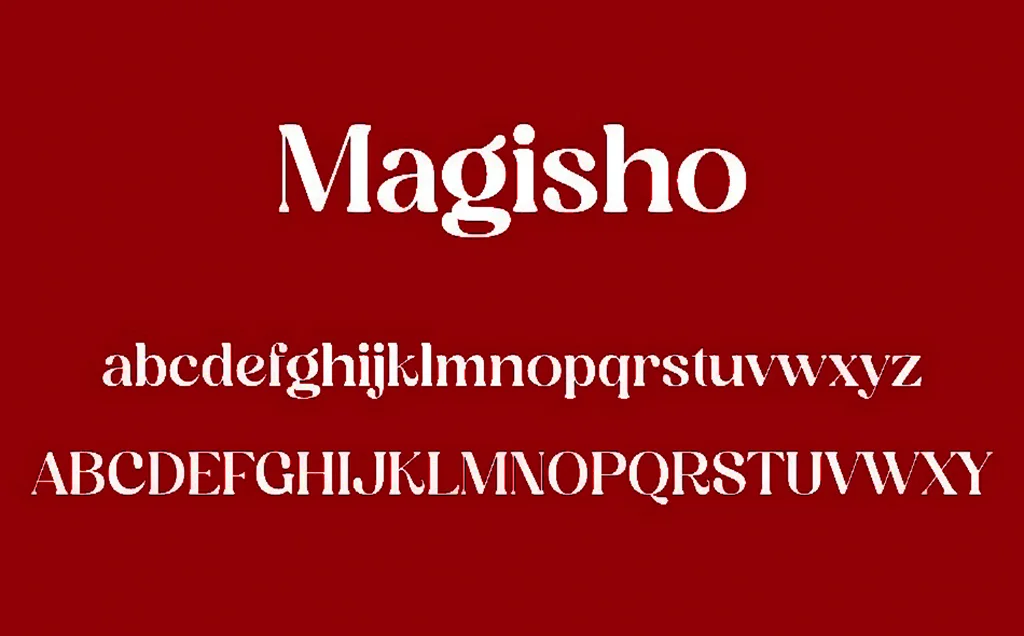
Magisho Font​
Font Storytype Studio tarafından 06.09.2022 tarihinde tasarlanmıştır. Font %100 Türkçe karakter uyumludur.
Kendine özgü tarzı ve modern görünümü olan serif, modern ve klasik bir yazı tipidir ayrıca zarif ve lüks bir logo, kitap veya film başlığı tasarımı, moda markası, dergi, kıyafetler, harfler, alıntılar ve çok daha fazlası...